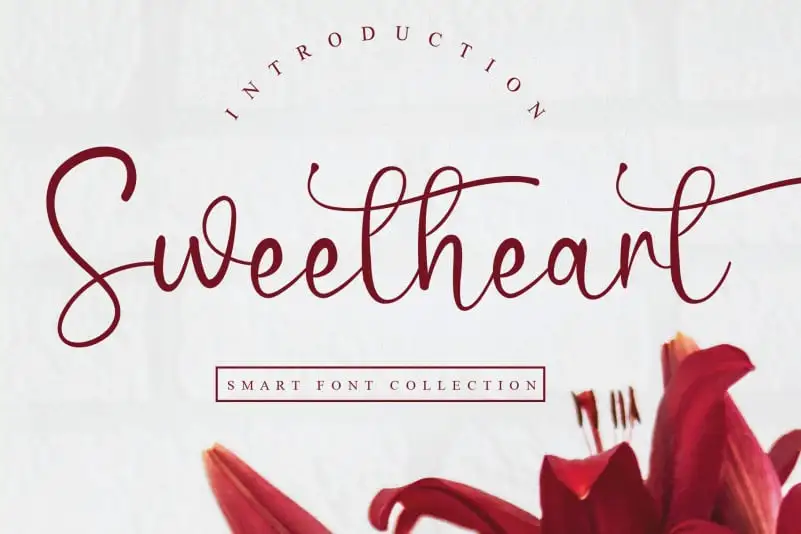
Sweetheart Calligraphy Font – Fonte Grátis
Sweetheart Calligraphy Font
Descubra Sweetheart Calligraphy Font, uma elegante seleção de caracteres feitos à mão para quem busca arte e sofisticação em cada projeto. Esta fonte é perfeita para aniversários especiais, cartas românticas ou qualquer outra ocasião que exige um toque delicado e poético. Com sua tipografia curvilínea e detalhes meticulosamente cuidados, Sweetheart Calligraphy Font oferece uma experiência única de escrita. Ideal tanto para o uso pessoal quanto para projetos profissionais como publicidade ou ilustrações, esta fonte é perfeita para quem valoriza a personalização em cada projeto. Sweetheart Calligraphy Font não apenas adicionará um charme especial ao seu design gráfico, mas também proporcionará uma experiência de escrita agradável e relaxante. Seja você criativo, poético ou ambas as coisas em um único projeto, Sweetheart Calligraphy é sua fonte ideal.